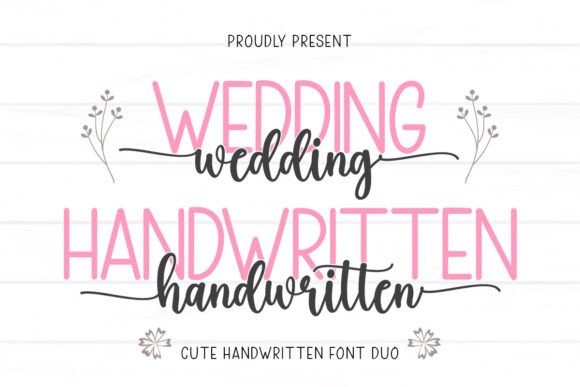
Wedding Handwritten
Encontrar los elementos de diseño adecuados puede ser un desafío, pero Wedding Handwritten ofrece una colección excepcional que eleva tu trabajo al instante.
Ya sea que estés creando productos POD (impresión bajo demanda), invitaciones de boda o gráficos para redes sociales, Wedding Handwritten es una opción ideal.